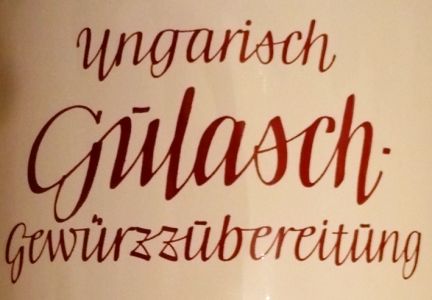
Schrift gesucht (Ostmann-Gewürze)
Ich wüsste zu gern, welche Schrift das ist.
Hab sie weder selbst erblättern können,
noch konnte ich sie mit FontExpert ermitteln.
Dies ist doch eine gezeichnete Schrift! Leichte Abweichungen
der g-, e-, z- und der ü/u-Formen, auch unterschiedliche
Schriftbreiten (bes. n) beweisen dieses. Da war wohl ein Schildermaler
oder Schaufensterdekorateur am Werk. Beim digitalisieren sollte von Sebastian unbedingt ein besseres Ergebnis dabei herauskommen.
Wie ja schon die Vorschreiber feststellten. Aber was meinst Du mit »besseres Ergebnis«? Der hänische Schriftzug ist doch sehr hübsch. Und was spricht gegen Buchstabenvarianten in einem digitalen Font? Das sollte die Sache doch bloß lebendiger machen und näher ans händische Vorbild brigen.
Natürlich würde ich Varianten und Verbindungen einbauen, mich hoffnungslos in Winzigkeiten verrennen, und nie mit der Schrift fertig werden... :roll:
Ich habe das Bild mal gespeichert in meinem Inspirationen-Ordner. Davor habe ich aber noch andere Schriften fertigzustellen. Mehr als 4 laufende Projekte müssen wirklich nicht sein...